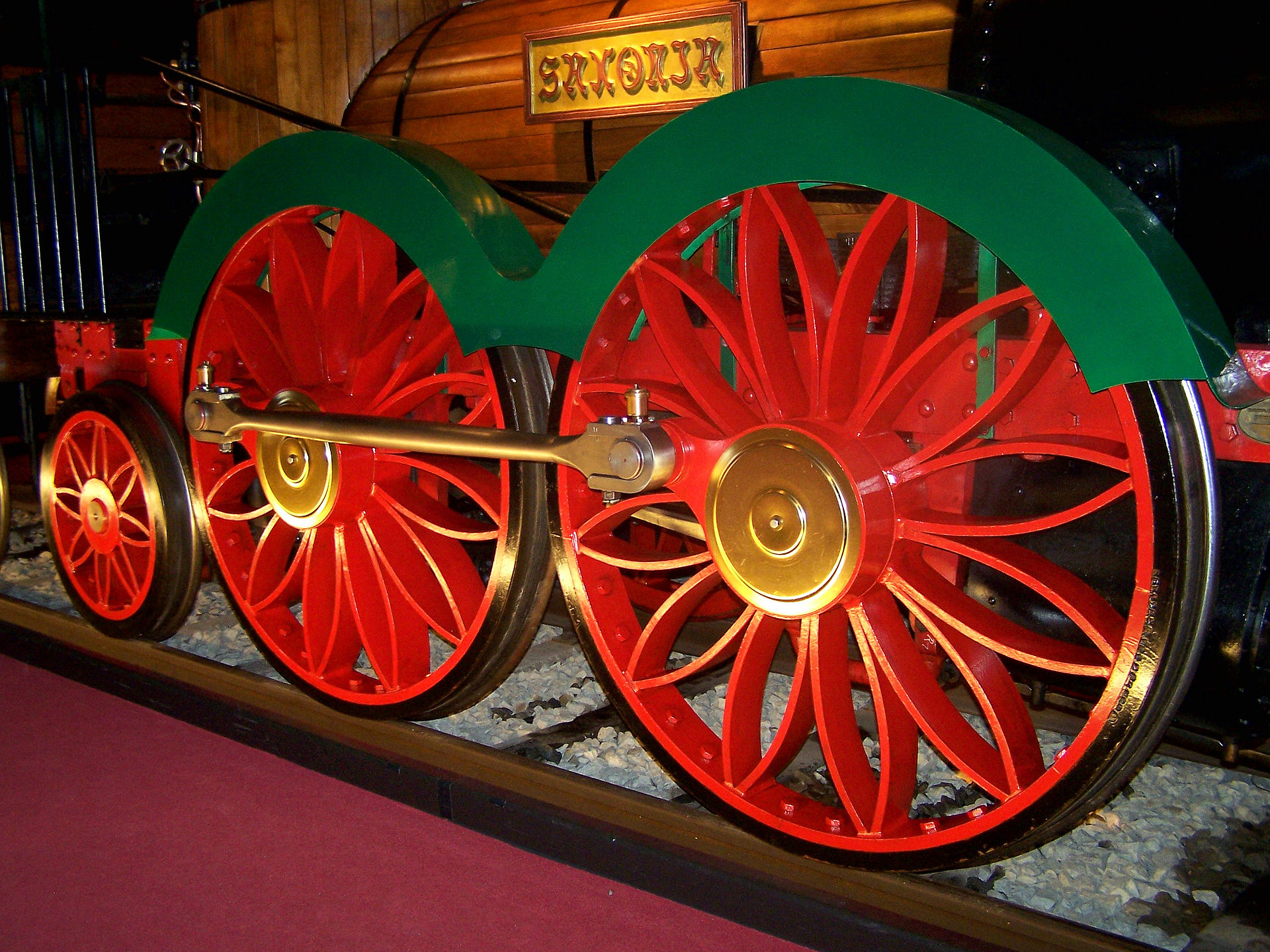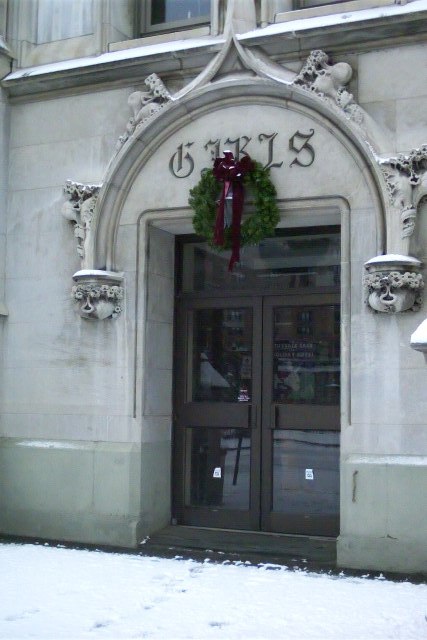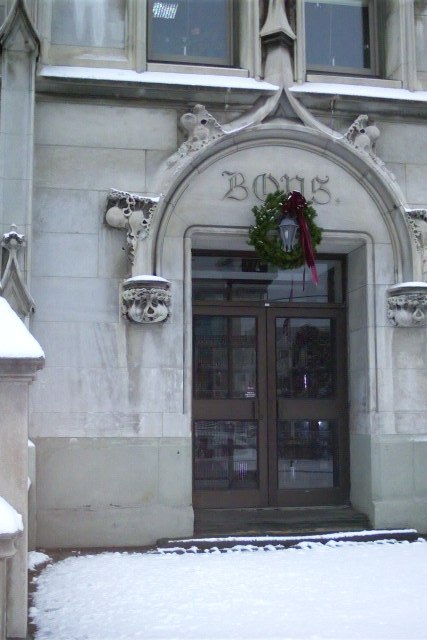
Du könntest ein paar Vokale kaufen: _A_O_IA
Eines der seltenen Beispiele des Fraktur-Versalsatzes
Also Blackletter-Versalsatz ist hier bei uns gar nicht soooo selten, sicher auch, weil es solch strikte Regeln wie in Deutschland hier nie gegeben hat.
Viel Spaß beim Entziffern
Also das verstehe ich jetzt nicht. :-? Ich dachte immer, Fraktur sei prinzipiell besonders leserlich. Wieso sollte man dieses Schild dann »entziffern« müssen – statt es ganz einfach zu lesen? :baeh:
Hinter die Boys hat man einen Punkt gemeißelt, bei den Girls hat man den eingespart. Klarer Fall von Diskriminierung.
Auf ihrer Wikipedia-Seite ist dieses Bild verlinkt, wonach der Nachbau wohl wirklich mit gebrochenen Versalien beschriftet ist.
Unten in der passenden Kategorie wären noch mehr Bilder, u.a. von einem Modell der Lok. Mir deucht, das Bild hier ist weder Nachbau, noch das dort zu sehende Modell?
Es gibt diverse Nachbauten und Modelle dieser Lok. Das Bild, was ich eingestellt habe, ist von einem Modell des Deutschen Museums, was vermutlich in den Siebzigern aufgenommen wurde.